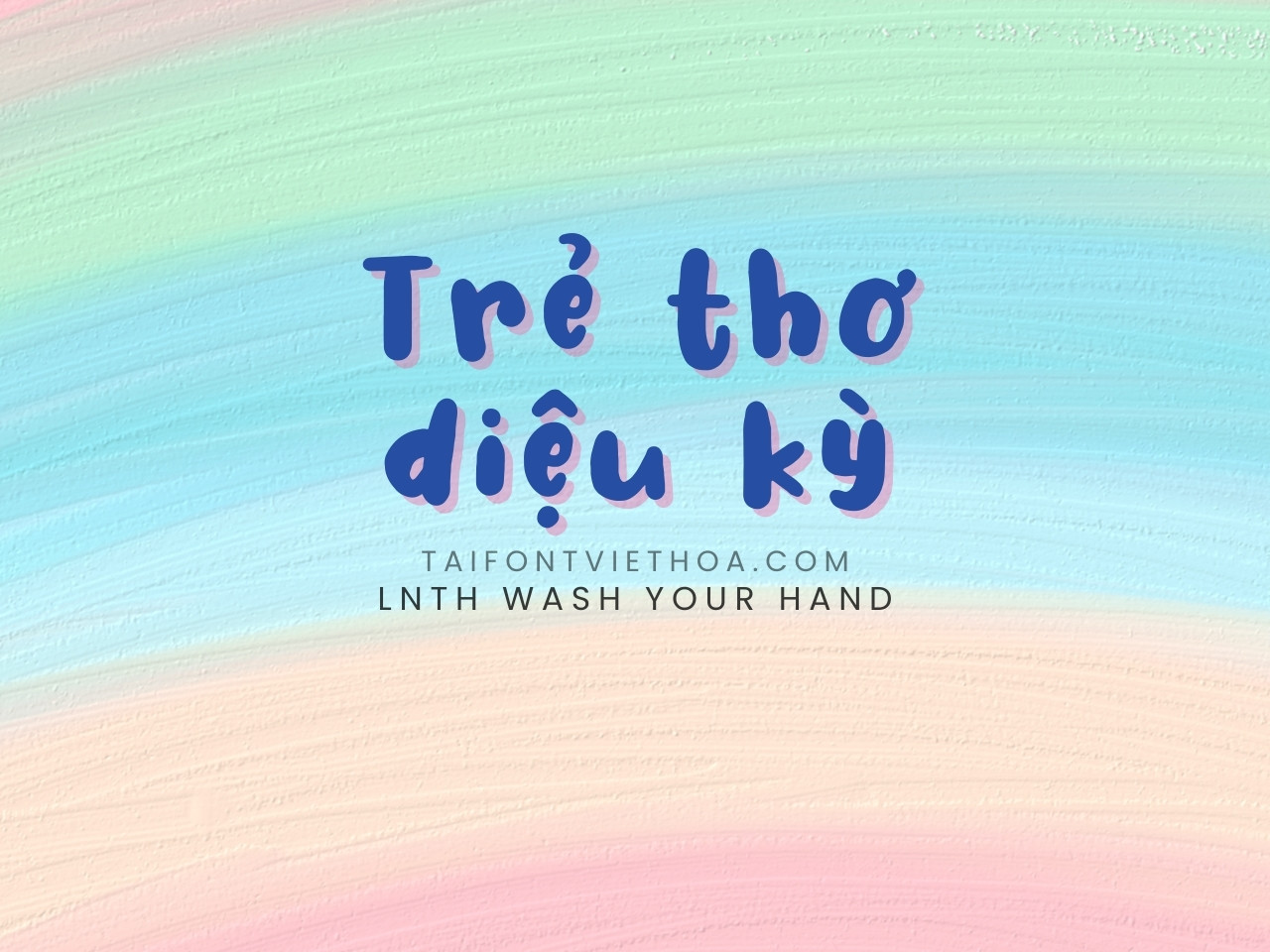
Font việt hóa LNTH Wash Your Hand
Tác giả Font: Khurasan
Giới thiệu về font LNTH Wash Your Hand – Cá tính, độc đáo và mang thông điệp thời đại
LNTH Wash Your Hand là phiên bản Việt hóa từ font gốc do Khurasan thiết kế – một font chữ viết tay phá cách, ra đời trong bối cảnh đại dịch COVID-19 như một lời nhắc nhở sáng tạo và đậm chất cá nhân. Phông chữ mang nét ngẫu hứng, gần như graffiti nhưng vẫn giữ được tính thẩm mỹ và khả năng đọc tốt. Tuỳn Pucca đã Việt hóa hoàn chỉnh font này, hỗ trợ đầy đủ tiếng Việt cùng hơn 60 ngôn ngữ khác, giúp mở rộng ứng dụng toàn cầu.
Font đã được taifontviethoa.com chọn lọc và thử nghiệm trong các thiết kế poster truyền thông cộng đồng, chiến dịch xã hội, hoặc các ấn phẩm dành cho lứa tuổi học sinh – sinh viên. Với phong cách đầy năng lượng và hơi hướng hiện đại, LNTH Wash Your Hand không chỉ là font chữ, mà còn truyền tải cảm xúc và nhận thức về thời điểm lịch sử đặc biệt.
Đặc điểm thiết kế và ứng dụng nổi bật của font LNTH Wash Your Hand
Font mang đặc trưng của kiểu viết tay tự do, kết hợp giữa script và handwritten với các nét gãy, liền mạch, không tuân theo cấu trúc truyền thống. Những chữ cái không đều nhau tạo cảm giác rất tự nhiên, mạnh mẽ và phá cách – rất phù hợp với các thiết kế cần tạo hiệu ứng thị giác nổi bật hoặc thể hiện thông điệp rõ ràng, sinh động.
LNTH Wash Your Hand phù hợp với nhiều ngành nghề như giáo dục, truyền thông xã hội, fanpage cộng đồng, game indie, hoặc các dự án thiết kế cá tính. Ứng dụng điển hình bao gồm: poster truyền thông, chiến dịch y tế cộng đồng, thiết kế sinh nhật sáng tạo, typography sự kiện hoặc tiêu đề bài đăng mạng xã hội mang thông điệp mạnh.